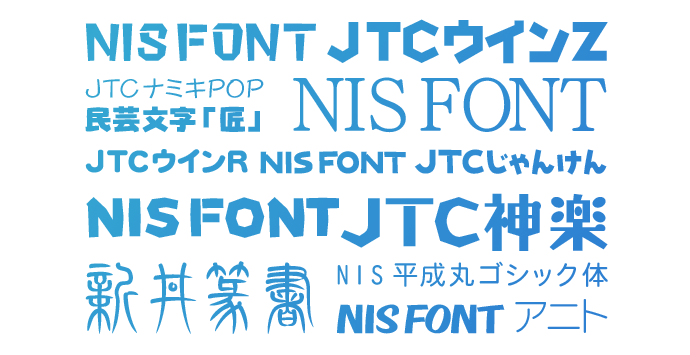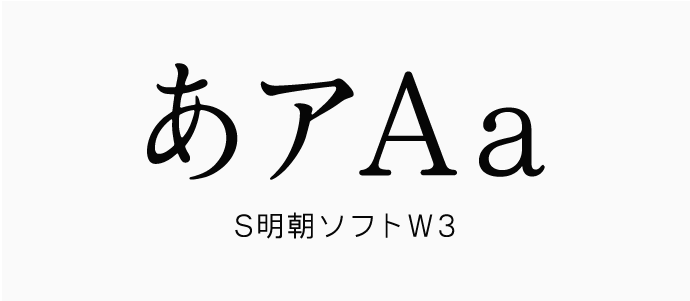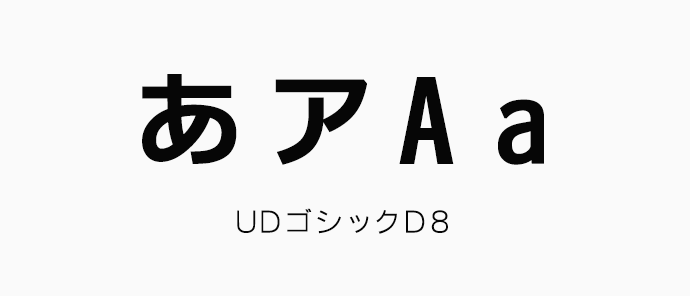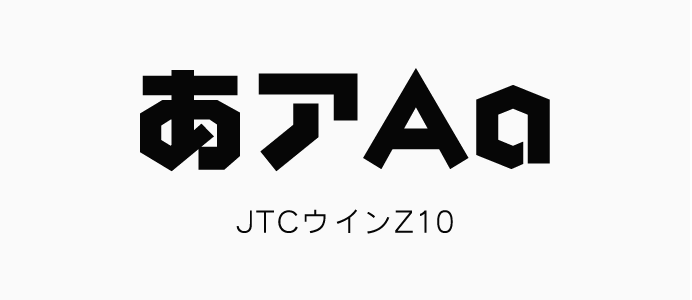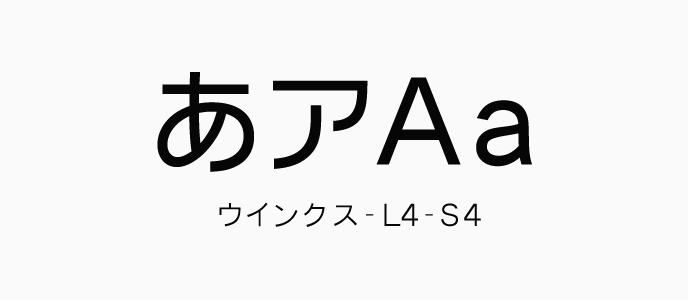
NIS Fontの魅力
より楽しく、より美しく想いを伝える。
NIS Fontは「より楽しくより美しく」をコンセプトに、お客様の伝えたい想いを、こだわりのフォントに変えてお届けします。
NIS Fontの歩み
1980年代初頭、米製CGソフトにて日本語を表示するために、日本で初めてパソコン用のアウトラインフォントを独自に開発し、DTPの発展に伴いパッケージ販売を開始しました。2000年代には、インターネットの普及に合わせてダウンロード販売を開始。現在も既存フォントとは異なる、ユニークかつ芸術性の高い新フォントの開発と、利用しやすいサービスを継続的に展開しています。プロ仕様のアウトラインフォントの他、デザイン素材など多彩な商材を取り揃えているのはもちろん、各企業製品へのOEM提供のほか、プロのデザイナーから一般ユーザーまで、幅広くご愛用いただいています。
NIS Fontの特色
特長的でオリジナリティあるPOP書体や、可読性・視覚性に優れたフォントを多数保有しています。各種広告媒体、バラエティ・ニュース等のTV番組、ゲームタイトル、書籍など使用実績も多数。また、ウエイトのバリエーション豊富さに加え、バランスに優れた美しい文字間も魅力のひとつです。書体デザインからデジタル化、ユーザーサポートまでワンストップの環境が整っており、オーダーメイドのフォント制作も可能です。
NIS Fontの主要書体
S明朝シリーズ
「柔らかなイメージと自然さ」をコンセプトにしたベーシックなフォルムです。文字の運びとかたちを大切にしているため、キャッチフレーズからボディコピー、エディトリアルなど、広告・雑誌、デザインをはじめ、幅広い分野でお使いいただけます。
NIS_UDゴシックシリーズ
どなたにも親しみやすい、クセのないフォーマル(基本)な書体です。デザイン性を全面に押し出し過ぎることなく、あらゆる場所や媒体での利用において、視認性・判読性が高く、読み手にとってより自然で優しいフォントに仕上げています。
JTCウインZシリーズ
100%直線のみで構成された、NIS Fontのなかでも人気を誇るゴシック体です。直線が持つ力強さを備えながらも、すっきりと見えるデザインはJTCウインZならでは。機械に頼らず手書きデザインですべてつくられた、デザイナー定番フォントです。
ウインクスL+JTCウインSシリーズ
「横組みに適した“かな“」をコンセプトにした横組み専用のフォルムです。漢字とかなの横と縦のラインが美しくそろうため、番組テロップやPOPチラシにも最適。
太さ(ウエイト)のバリエーション(ファミリーフォント)を4種類ご用意しています。